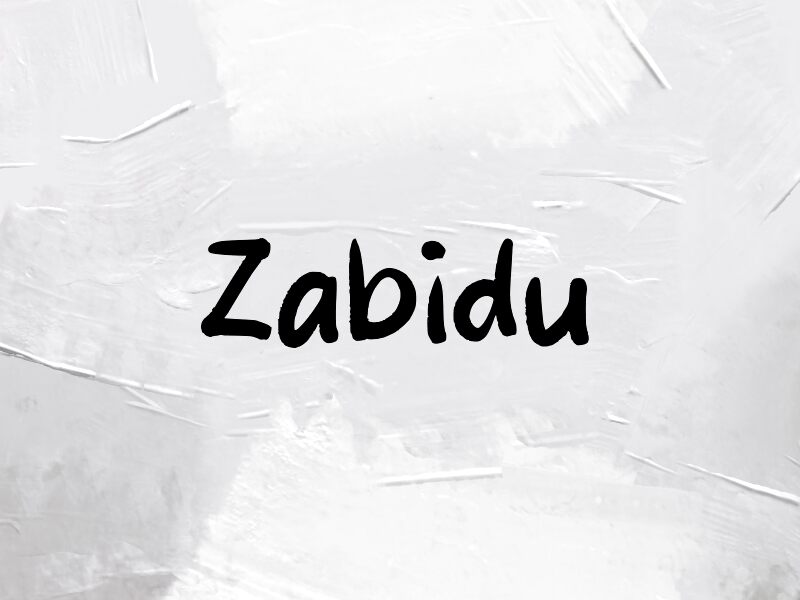
Zabidu, créée par Wep, est une police pinceau gratuite au rythme fluide et peint à la main, dotée de traits épais et arrondis. Ses lettres évoquent la spontanéité et la décontraction, avec des courbes franches, un rythme irrégulier et des bords légèrement bruts qui confèrent à l'ensemble une chaleur authentique, loin du lissage artificiel.
C'est un choix tout indiqué pour les titres d'affiches, l'image de marque de cafés, le packaging, les en-têtes de réseaux sociaux et les visuels d'événements courts, là où l'aspect humain prime sur la rigueur formelle. En tant que police gratuite, elle est également parfaite pour les textes de couverture, les ébauches de logos et autres compositions rapides, car la largeur de ses formes pinceau rend les mots, même courts, vivants et percutants.
Zabidu